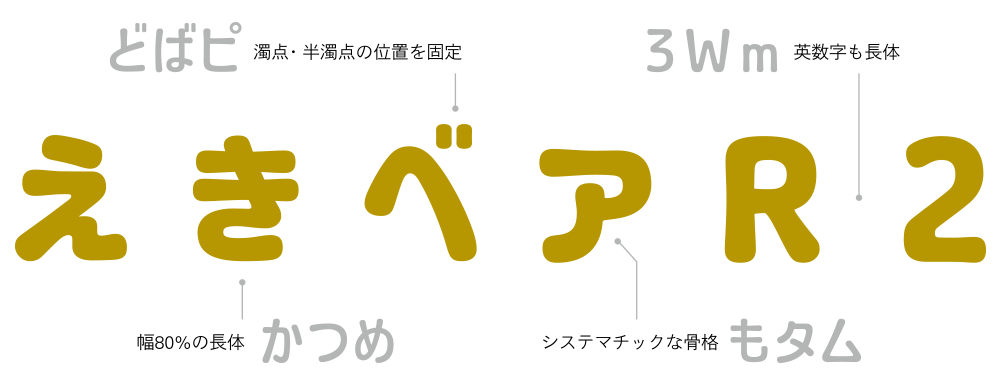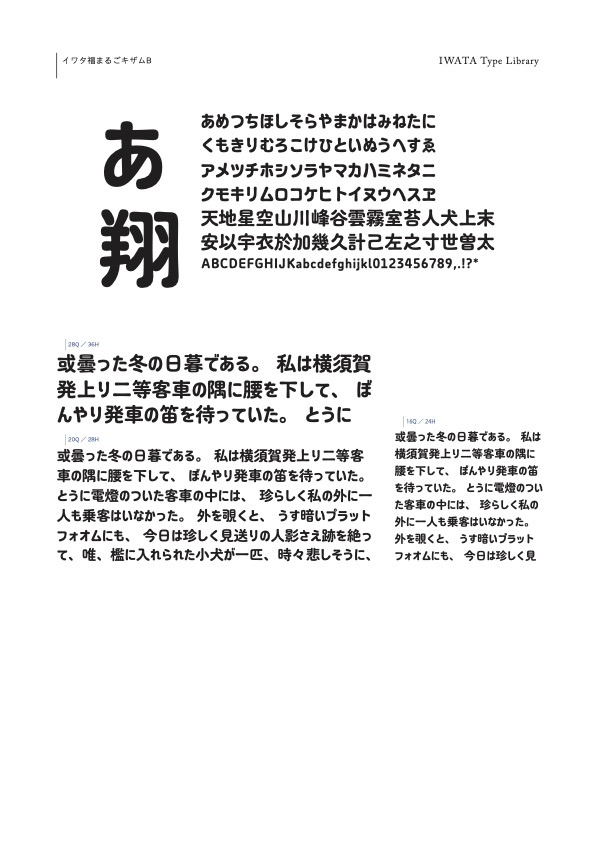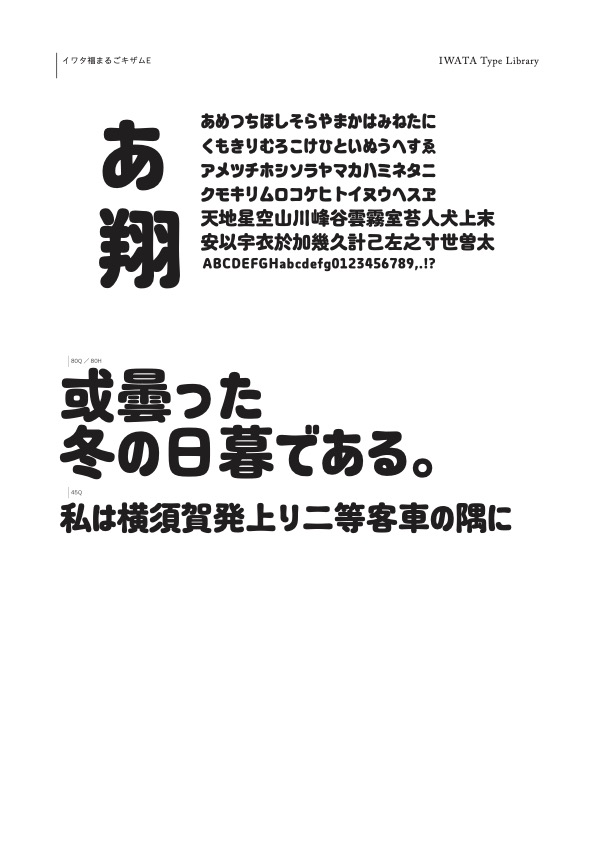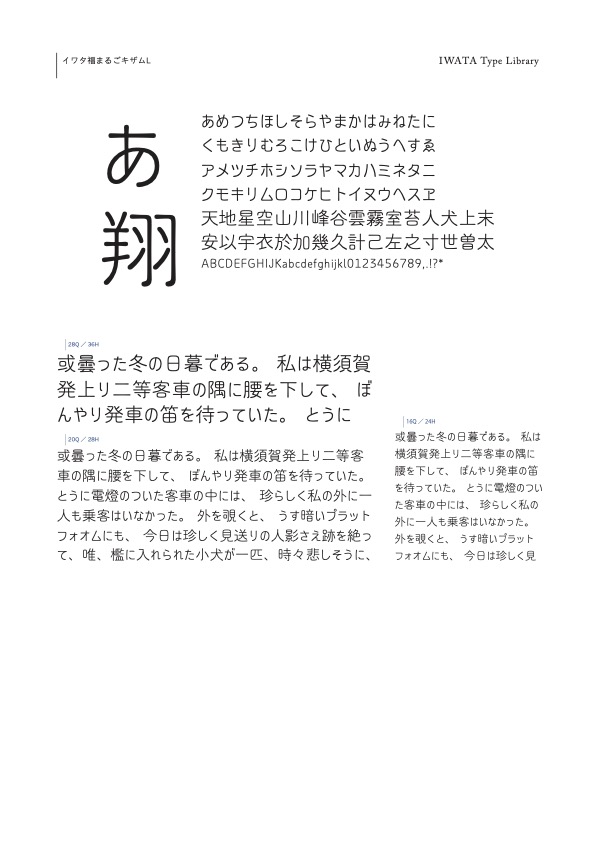
有機的な曲線が特徴のイワタ福まるごのバリエーション書体です。
水平垂直に構成された長体かなを、横方向のラインに沿って揃えた機械彫刻のような書体です。
タイプライターで規則正しく打たれたような律儀さに柔らかい曲線が合わさり、整然としていながら堅苦しくない印象を刻みます。
※キザムは横組み専用の書体です。